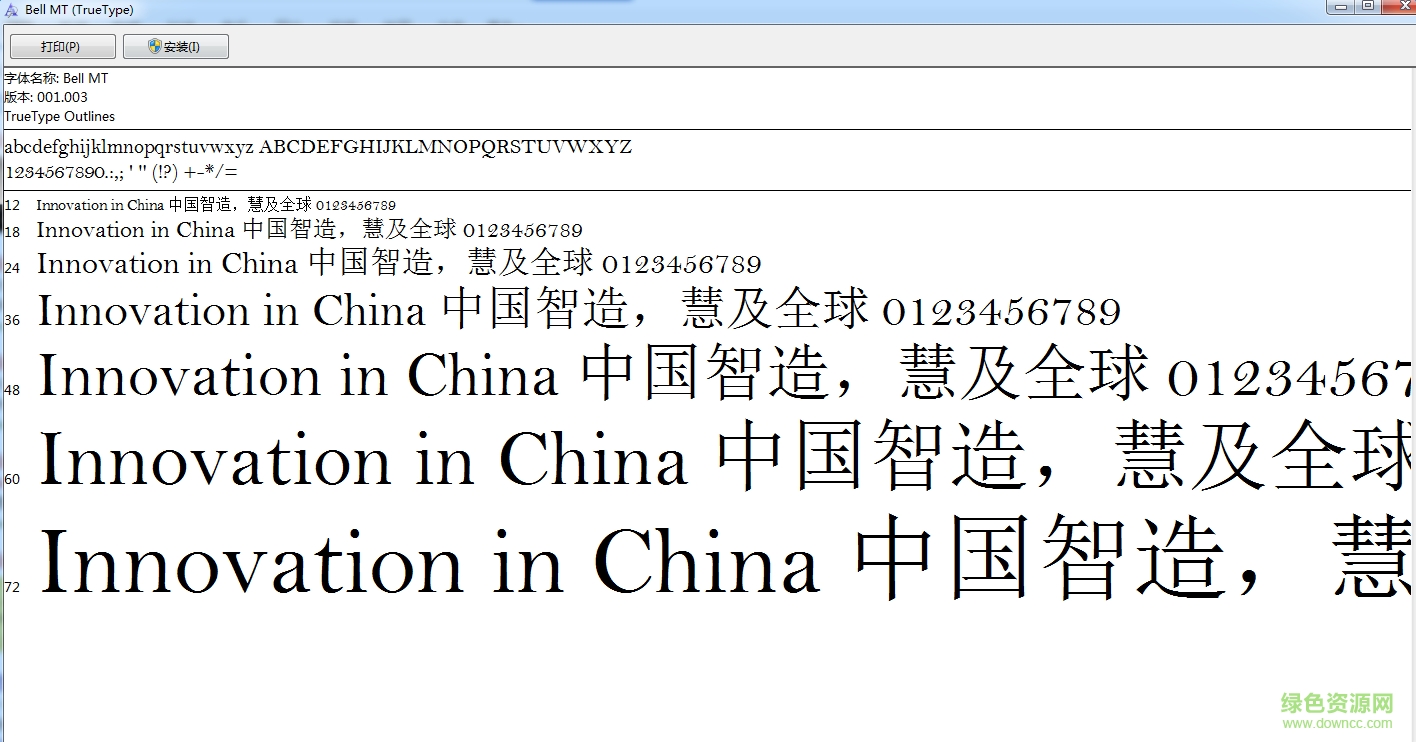
bellmt
bell mt字體是一款常見的英文襯線字體,字型秀美,字體婉轉(zhuǎn)有度,線條流暢灑脫,閱讀效果清晰明朗,需要的朋友歡迎在綠色資源網(wǎng)下載!
bellmt字體筆形柔和,清秀工整,筆劃纖細(xì),結(jié)構(gòu)均勻,可以應(yīng)用于標(biāo)題、廣告制作、裝飾裝幀等各種領(lǐng)域!